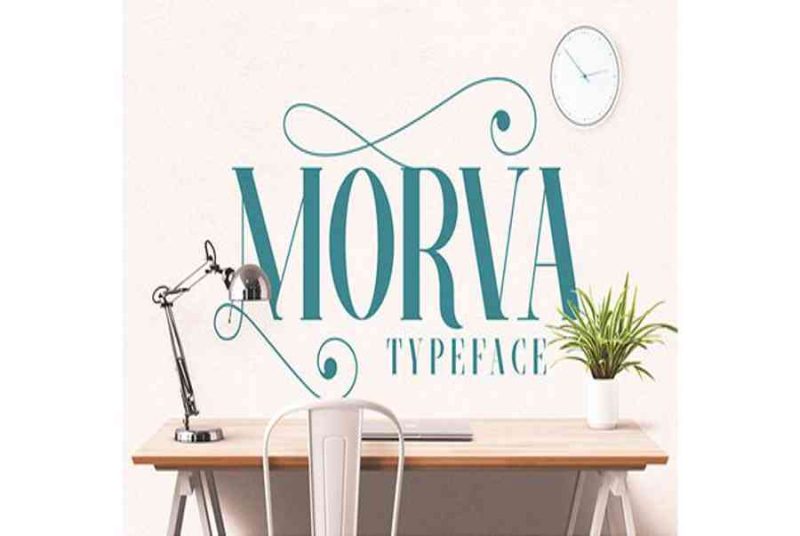
Cho dù bạn yêu thích sử dụng những font chữ thú vị, vui nhộn cho công việc của mình hay chỉ đơn giản là sử dụng hàng ngày, danh sách font chữ phải có từ kiểu serif cho đến kiểu script và nhiều hơn nữa sẽ rất phù hợp với bạn. Tại Envato Market, bạn sẽ có thể tìm thấy những font chữ tuyệt vời bên dưới cho phù hợp với các sự cần thiết trong thiết kế của bạn..
Chữ nét mảnh (Serif)
Serifs là phông chữ tuyệt vời cho toàn bộ những nhu yếu chuyên nghiệp, phong thái của bạn. Font chữ này có ảnh hưởng tác động một cách tuyệt vời so với tên thương hiệu công ty, truyền thông online in ấn, và một loạt những nhu yếu phông chữ khác. Tôi đặc biệt quan trọng thích Serifs cho những logo phong thái .
Font chữ này phối hợp bởi cấu trúc tự nhiên với độ cứng của kiểu serif. Tôi rất thích font chữ này để thêm tạo điểm nhấn kiểu homemade vào phong cách thiết kế vỏ hộp hoặc in ấn cần cảm xúc hữu cơ, nuôi trồng tại nhà .
Phông chữ này là tuyệt vời khi bạn cần một cái nhìn kiểu máy đánh chữ cổ cho thiết kế của bạn. Tôi đặc biệt thích cách thể hiện chi tiết trong các mẫu chữ không đồng nhất mà một máy đánh chữ thực sự sẽ tạo ra.
Phông chữ này gồm có hai bộ phong thái : một loại thì hơi kiểu serif và loại kia thì có những nét cong ấn tượng. Chúng trộn lẫn với nhau một cách tuyệt vời đề tạo cho văn bản một diện mạo phong thái, ấn tượng .
Phông chữ serif theo phong thái vintage rất tương thích cho những logo và phong cách thiết kế in ấn ( đặc biệt quan trọng là quần áo ). Với phong thái in tay xen kẽ và Tặng Ngay thêm 1 số ít vectơ, phông chữ này cung ứng cho bạn mọi thứ bạn cần để tạo ra một số ít phong cách thiết kế cổ xưa tuyệt vời .
Bộ sưu tập serif sẽ là gì mà không có một số ít phông chữ slab serif in đậm ? Qumberland là một sự bổ trợ rõ ràng cho bất kỳ bộ sưu tập phông chữ của nhà phong cách thiết kế nhưng không mạnh như font chữ slab serif thường thì .
Font chữ serif lấy cảm hứng thời trang này là một sự bổ trợ tuyệt với cho bất kỳ bộ sưu tập font chữ nào tập trung chuyên sâu vào việc tạo ra những tiêu đề hoặc phong cách thiết kế in ấn phát minh sáng tạo. Sự trộn lẫn giữa những nét dày và mảnh chắc như đinh sẽ tạo nên một bộ những glyph xuất sắc
Font chữ serif này cho ta một cảm xúc retro ngộ nghĩnh trong khi vẫn giữa được phong thái sành điệu. Với rất nhiều glyph để lựa chọn, Violina chắc như đinh sẽ tạo cho bản vẽ của bạn một diện mạo độc lạ .
Quincy là một mái ấm gia đình phông chữ xinh đẹp, sang chảnh với sự tương hỗ đa ngôn ngữ, chữ in nghiêng, và nhiều hơn nữa. Khi bạn đang cần một serif thay thế sửa chữa cho những font chữ thường thì, một phông chữ lịch sự như Quincy trong bộ sưu tập của bạn chắc như đinh là font chữ số 1 .
Morva không chỉ Open với những mẫu chữ lịch sự mà còn có những nét cong bay bướm ngộ nghĩnh dưới dạng kiểu chữ MORVA biến hóa cho nhau .
Goldsmith chắc như đinh là một serif mê hoặc. Với những nét chữ hoa và thường xen kẽ và mẫu chữ handmade cẩn trọng, font chữ này là một câu vấn đáp tuyệt vời để tổng hợp hình ảnh in máy độc lạ cho nhiều loại việc làm phong cách thiết kế .
Script
Phông chữ script trải dài từ viết tay đến những tác phẩm kiểu chữ thư pháp. Chúng rất tuyệt để dùng cho các logo sáng tạo, tiêu đề, và thiết kế áo thun. Hãy mang về bộ sưu tập font chữ dưới đây để thưởng thức một vài font chữ yêu thích của tôi nhé.
Bạn sẽ thấy font chữ này bên dưới những font chữ serif, tuy nhiên đây là một kiểu chữ viết script bằng cọ bóng bẩy mà tôi rất khuyên bạn sử dụng cho tên thương hiệu, nội dung tiếp thị quảng cáo xã hội, và nhiều hơn nữa .
Toi rất thích cọ kiểu chữ script này. Một nét phẳng, đậm tạo ra mỗi dạng chữ cho phong thái vẽ tay, điển hình nổi bật tuyệt vời mà ít người hoàn toàn có thể tự tạo ra được .
Các vần âm của Humble Script nhảy nhót trên bất kể những trang, màn hình hiển thị hoặc nội dung mà bạn tạo ra với nó. Hoàn hảo cho những tài liệu tiếp thị hoặc những mẫu logo, kiểu script này tạo cho ta cảm giác ngộ nghĩ và vẽ tốc ký .
Moonface Script là câu vấn đáp xuất sắc cho những font chữ script theo kiểu bóng chày và thể thao. Tuyệt vời cho y phục và những việc làm phong cách thiết kế khác, phông chữ này có một số ít hình dạng cái roi lớn trong khuôn khổ dạng chữ của nó .
Những font chữ script tròn, lớn là cần có trong bộ sưu tập của nhà phong cách thiết kế. Người yêu font chữ kiểu nào cũng hoàn toàn có thể nhìn nhận cao những tùy chọn phong thái trong phông chữ kiểu mở này .
Những font chữ dạng vẽ cọ khô là một sự bổ trợ tuyệt vời cho bộ sưu tập của bạn danh cho những tài liệu tiếp thị và phong cách thiết kế in ấn. Akula là một ví dụ nổi bật cho phong thái đó .
Đối với một phong thái viết tay phức tạp hơn, Merno Script là phông chữ dành cho bạn. Các logo, tiêu đề, và nhiều hơn nữa là một sự thay thế sửa chữa nhanh gọn với kiểu chữ viết lịch sự này .
Tôi yêu font chữ kiểu cọ viết tay này. Một phông chữ như thế này rất tuyệt vời khi đi cùng với cấu trúc màu nước hay màu mực, được cho phép người dùng bắt chước một phong thái handmade thực sự .
Kết thúc
Danh sách font chữ này hướng tới nhấn mạnh sự hữu dụng và nội dung cần có cho các nhà thiết kế đồ họa và những người yêu thích font chữ. Rất có thể chúng ta đã bỏ lỡ một vài món trong Envato Market mà bạn nghĩ sẽ là một công cụ xuất sắc cho hộp dụng cụ của bất kỳ nhà thiết kế nào. Chia sẽ những link này trong phần bình luận bên dưới, và hãy để danh sách này là một điểm khởi đầu để xây dựng bộ sưu tập phông chữ nền tảng của bạn!